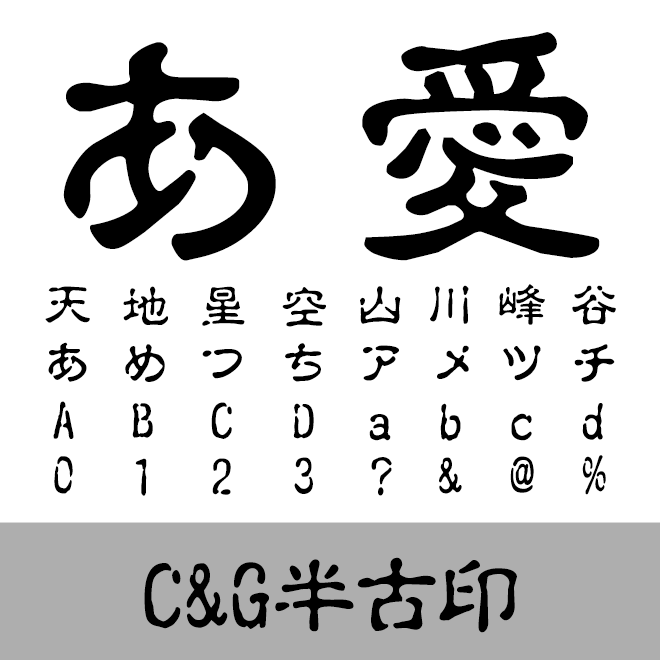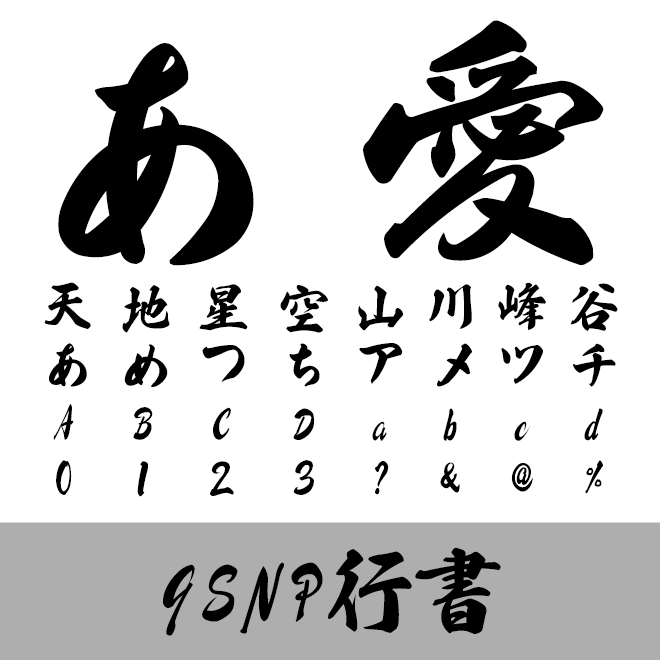
デザイン初心者にもプロにも嬉しい、5,000円以下のお手頃フォントを特集しました。本文用の明朝体やゴシック体、手書き風フォント、さらに個性が光るデザイン書体まで幅広くラインナップ。
お手頃 本文書体
デザインポケットでは、本文に最も使われる明朝体やゴシック体、丸ゴシック体などのフォントを「本文書体」と呼んでいます。
本文書体は、文書全体の雰囲気を決める大切な役割を持ち、長時間読んでも疲れにくいよう可読性を優先してデザインされているのがポイントです。そのため、書籍やウェブページ、チラシなどの文章にぴったりです。
適切な本文書体を使うことで、情報が伝わりやすくなり、読み手の興味を引きやすくなります。
かもめ明朝
文字魚/Typographish
かもめ明朝
優しく温かみのある明朝体で、金属活字が着想源。
AR明朝体U
アーフィック
AR明朝体U
極太デザインの明朝体で見出しに最適。
TA明朝GF
スキルインフォメーションズ
TA明朝GF01〜03
POPや見出し、案内状など多用途に使える明朝体。
ARゴシック体S
アーフィック
ARゴシック体S
極太で存在感抜群の定番ゴシック体。
AR新藝体U
アーフィック
AR新藝体E/H/U
おしゃれで視認性の高いゴシックベースの書体。
スキルインフォメーションズ
TA角シャドー
影付きの袋文字デザインでインパクトのあるゴシック体。
AR丸ゴシック体
アーフィック
AR丸ゴシック体M/E
本文/見出しそれぞれに適した太さが特徴の丸ゴシック。
TA重ね丸ゴ
スキルインフォメーションズ
TA重ね丸ゴ
立体感を演出する丸ゴシック体のラインデザイン。
TA丸ゴ
スキルインフォメーションズ
TA丸ゴGF01〜05
シンプルな丸ゴシック体でPOPや案内状に最適。
お手頃 楷書体
楷書は、美しい筆の流れを感じさせる、整った形が特徴のフォントです。伝統的な手書きの美しさを活かしつつ、現代のデジタル環境でも使いやすい設計となっています。
案内状や名刺、公式文書など、フォーマルな場面で使用することで、上品さと信頼感を演出できます。柔らかな線と落ち着いた印象で、あらゆるデザインに調和します。
藍原筆文字楷書
Faraway
藍原筆文字楷書
和風テイストの細めで落ち着いた楷書体。
AR顏眞楷書体H
アーフィック
AR顏眞楷書体H
顔眞卿の書を基にした力強い楷書体。
AR楷書体M
アーフィック
AR楷書体M
正統派の楷書体で筆文字の基本。
お手頃 行書・古印・隷書・篆書
行書や古印、隷書、篆書は、伝統文化や歴史を感じさせる個性的な書体群です。行書の流麗な曲線、古印体の趣ある文字形、隷書の安定感、篆書の荘厳さなど、それぞれが独自の魅力を持っています。
これらの書体は、和風デザインや歴史をテーマにした作品、落ち着いた雰囲気を演出する広告などで重宝されます。特定のテーマにマッチすることで、デザインの訴求力を高められます。
AR行楷書体
アーフィック
AR行楷書体L/H
楷書体と行書体の中間で柔らかな印象。
TA優美毛筆行書
スキルインフォメーションズ
TA優美毛筆行書
優雅で美しい行書体。挨拶状に最適。
GSNP行書
システムグラフィ
GSNP行書M/B
デザイン性が高く、上品な印象の行書体。
AR古印体
アーフィック
AR古印体B
古印の風合いを再現したクラシックな書体。
g_コミック古印
よく訓練されたフォント屋
g_コミック古印体EL〜H
コミック向けに調整された読みやすい古印体。
C&G半古印
シーアンドジィ
C&G半古印
古印体の伝統に新感覚をプラスした可愛らしい書体。
AR隷書体